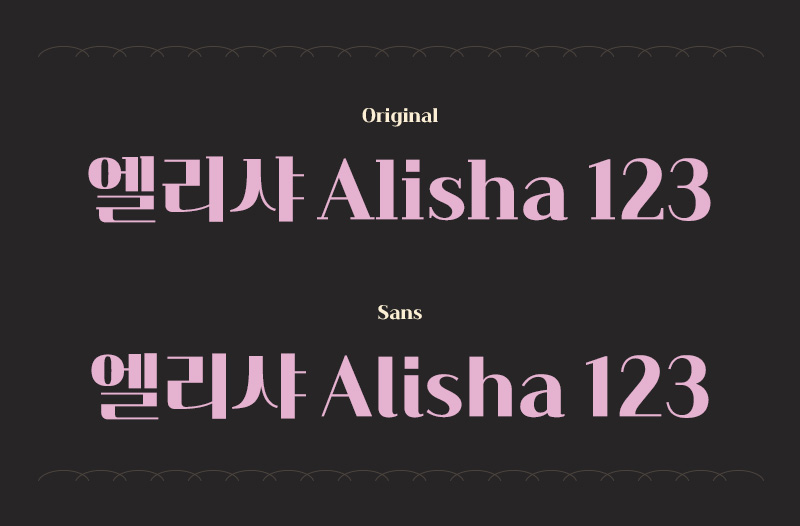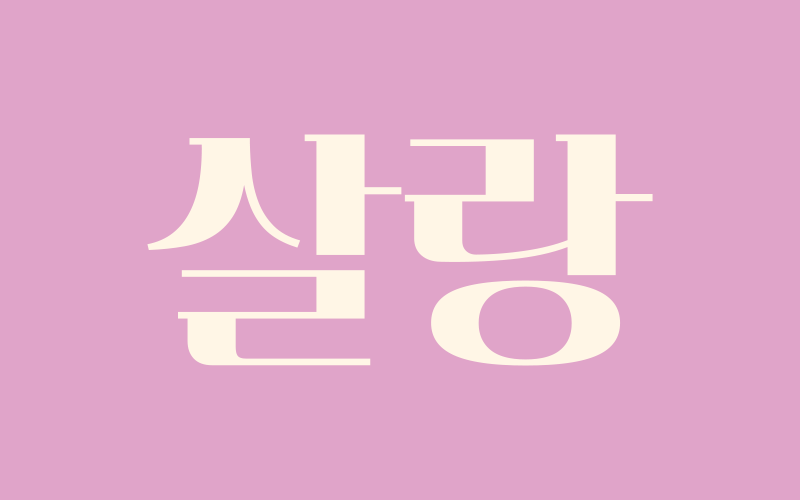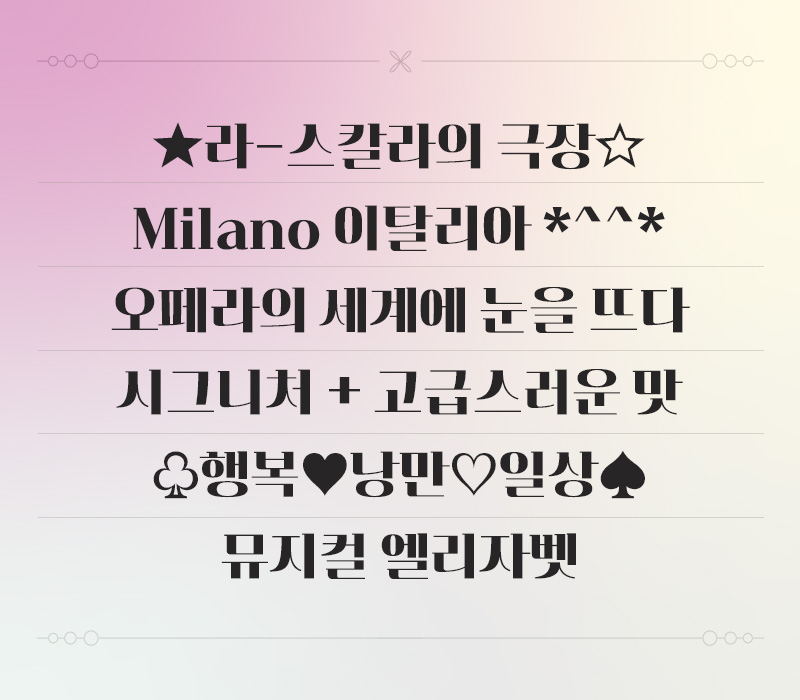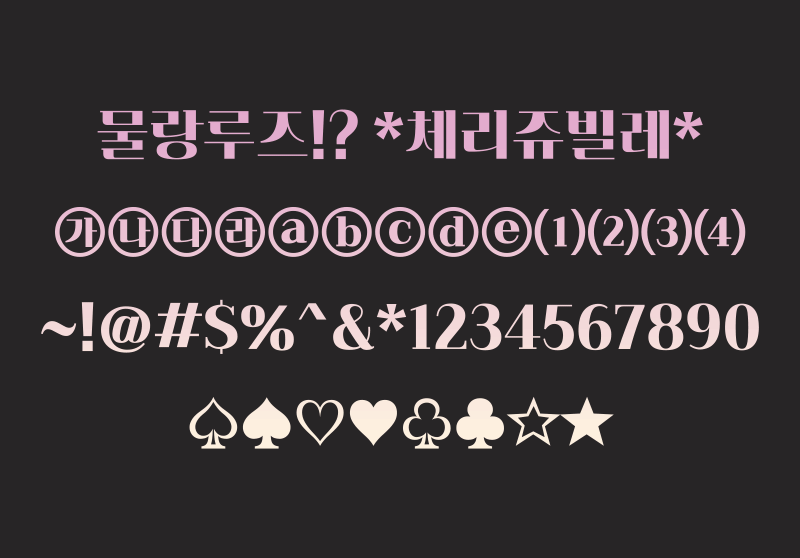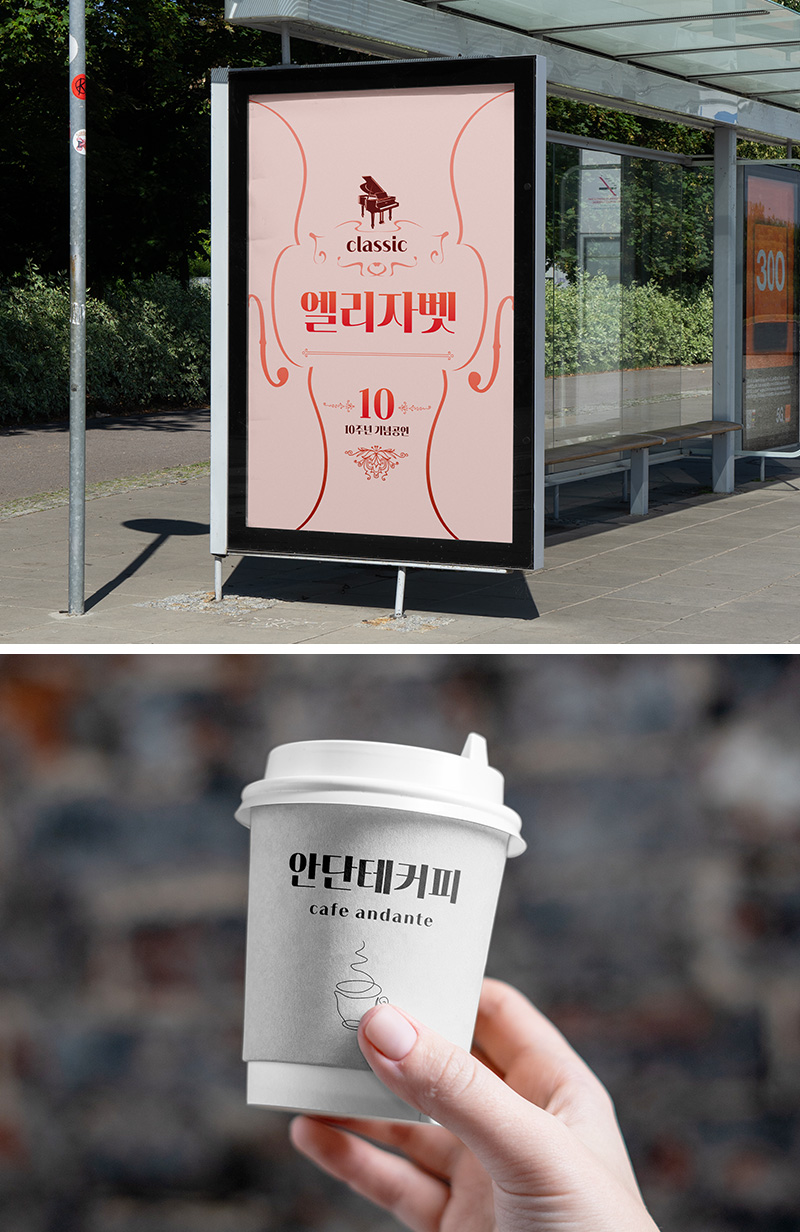
RixEnsemble
2 Style - Original, Sans
강한 획대비와 유려한 곡선으로 우아한 인상을 가진 서체입니다.
모던한 세리프 디자인의 Original과 깔끔하고 부드러운 Sans 2종으로 제작되었습니다.
고급스럽고 세련된 이미지로 주목도가 필요한 다양한 매체에 사용할 수 있습니다.
Original
꽃처럼 피어나 별처럼 빛나는 그대에게
Sans
꽃처럼 피어나 별처럼 빛나는 그대에게
세리프(오리지널)와 산세리프 2종으로 제작하여 사용성을 넓혔습니다.
유려한 곡선으로 부드러움을 가미했습니다.
영문, 약물의 디자인은 한글과 동일한 특징을 가지고 있어 혼용 시 조화롭습니다.